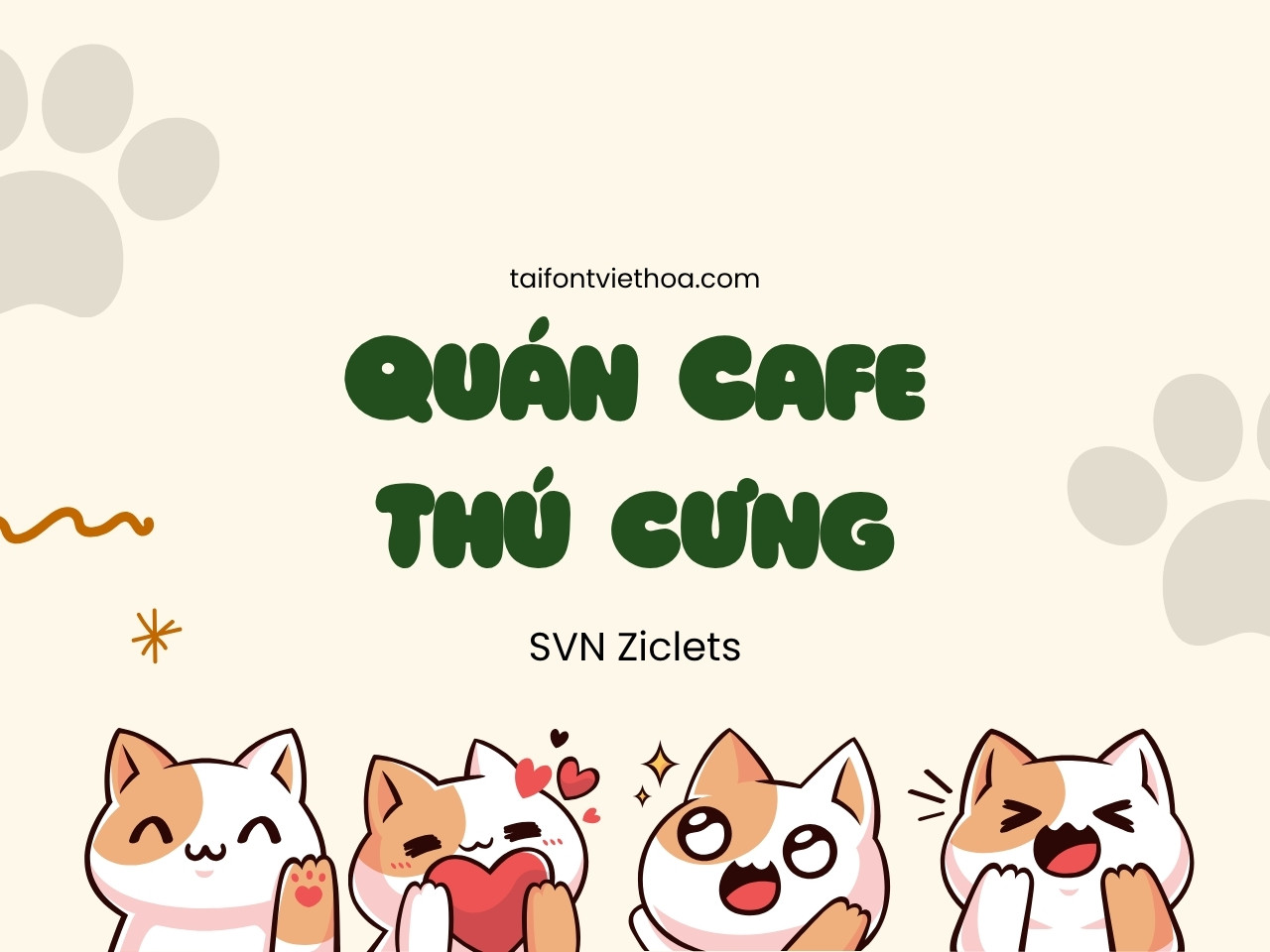
Giới thiệu về font SVN Ziclets – Tinh nghịch, ngộ nghĩnh và đầy màu sắc trẻ thơ
SVN Ziclets là phiên bản Việt hóa của font Ziclets – một kiểu chữ sans-serif siêu dễ thương với phong cách trẻ trung, ngộ nghĩnh và vui nhộn. Font được lấy cảm hứng từ những viên kẹo, đồ chơi và thế giới đầy màu sắc của trẻ thơ, mang lại cảm giác vui vẻ, đáng yêu và giàu tính biểu cảm. Thiết kế nguyên bản được phát hành bởi Creative Fabrica, chuyên phục vụ cho các dự án thiết kế liên quan đến trẻ em, sản phẩm thiếu nhi hoặc chủ đề lễ hội.
Phiên bản Việt hóa SVN Ziclets được chăm chút cẩn thận, đảm bảo hỗ trợ đầy đủ dấu tiếng Việt và tương thích với hơn 60 ngôn ngữ quốc tế khác. Tải Font Việt Hóa đã lựa chọn, tinh chỉnh và chia sẻ font này như một phần trong bộ sưu tập các font sáng tạo dành cho nhà thiết kế, đặc biệt là những người đang làm việc trong lĩnh vực giáo dục, giải trí thiếu nhi hoặc các sản phẩm mang tính vui tươi, thân thiện với người dùng.
Đặc điểm thiết kế đáng yêu – Lý tưởng cho các dự án dành cho trẻ em và thiết kế vui nhộn
SVN Ziclets có cấu trúc sans-serif bo tròn, nét chữ to đều, các góc được xử lý mềm mại giúp tạo cảm giác gần gũi và đáng yêu. Tỷ lệ chữ hài hòa với x-height cao giúp dễ đọc ngay cả ở cỡ nhỏ, trong khi thiết kế tổng thể lại đủ nổi bật khi dùng làm tiêu đề hoặc trên bao bì sản phẩm. Font mang lại sự linh hoạt trong truyền tải cảm xúc tích cực và thân thiện trong các thiết kế sáng tạo.
Ứng dụng lý tưởng: sách tranh thiếu nhi, poster trường học, thiết kế bao bì bánh kẹo, quần áo trẻ em, đồ chơi, thiệp mời sinh nhật, hoặc giao diện ứng dụng học tập cho trẻ nhỏ. Ngành nghề phù hợp: giáo dục mầm non, giải trí thiếu nhi, sản phẩm gia đình, thương hiệu đồ chơi, và ngành hàng tiêu dùng vui nhộn.